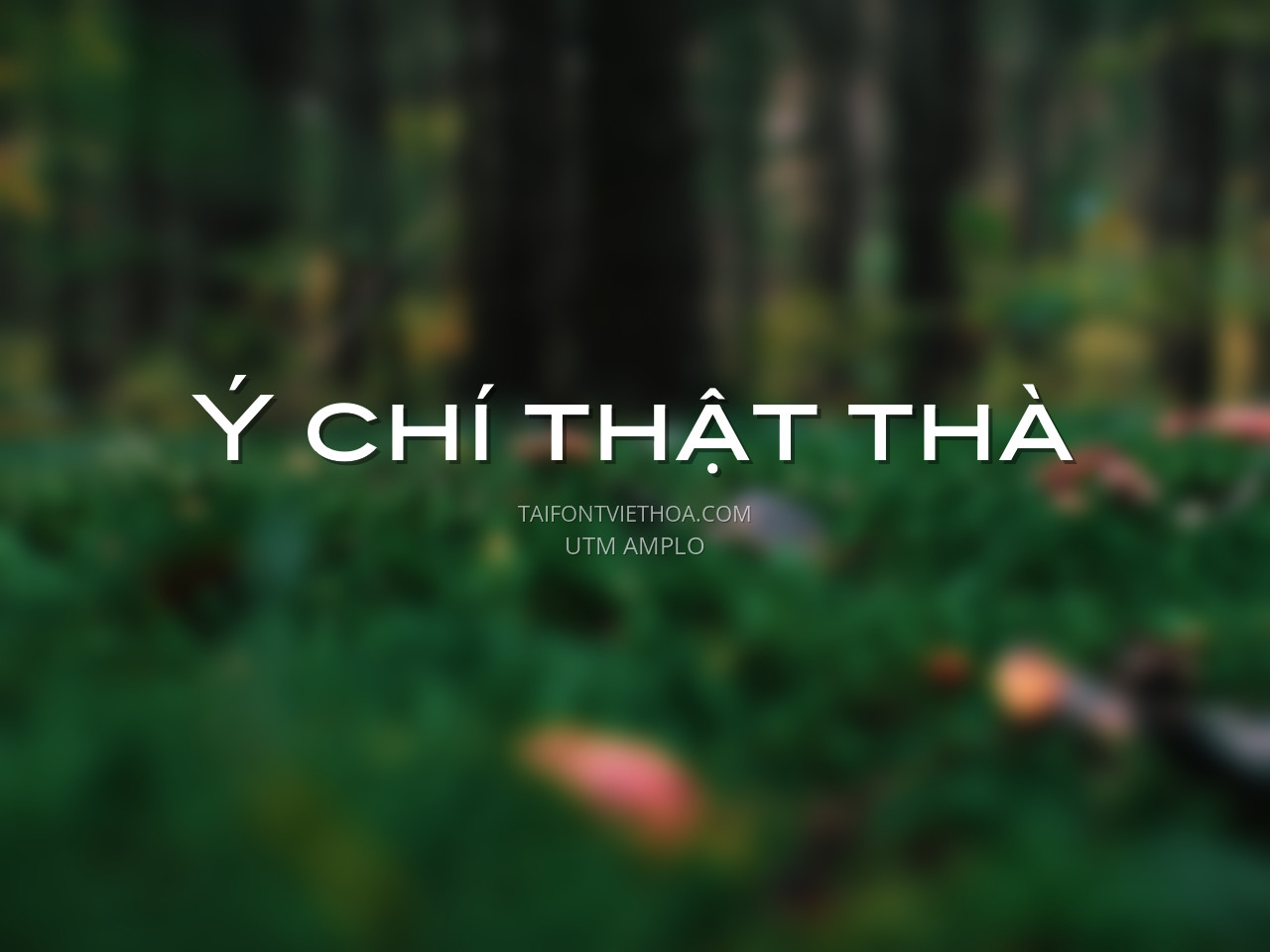
Font việt hóa UTM Amplo
Giới thiệu về font UTM Amplo
UTM Amplo là phiên bản Việt hóa của font Amplo – một kiểu chữ sans-serif hiện đại, thanh lịch và dễ đọc, được thiết kế bởi nhà thiết kế typographic hàng đầu của châu Âu. Font gốc nổi bật với cấu trúc chữ đơn giản, hình khối cân đối và các đường nét mềm mại, mang đến sự tinh tế và chuyên nghiệp cho các thiết kế hiện đại. Phiên bản Việt hóa được phát triển để hỗ trợ đầy đủ tiếng Việt cùng hơn 200 ngôn ngữ khác, giúp mở rộng khả năng ứng dụng trong nhiều dự án thiết kế đa dạng.
Đặc điểm thiết kế và ứng dụng của UTM Amplo
UTM Amplo sở hữu cấu trúc sans-serif không chân, các nét chữ có độ dày trung bình, hình khối gọn gàng và khoảng cách ký tự được căn chỉnh hợp lý. Font mang đến sự cân đối và dễ đọc trên nhiều kích thước và bối cảnh sử dụng khác nhau. Thiết kế đơn giản nhưng tinh tế, phù hợp với nhiều loại hình thiết kế từ nhận diện thương hiệu đến nội dung số.
Font thích hợp sử dụng trong thiết kế website, logo, bao bì sản phẩm, brochure, poster, và các dự án marketing kỹ thuật số. Các ngành nghề phù hợp gồm: công nghệ, truyền thông, giáo dục, startup và thương mại điện tử.